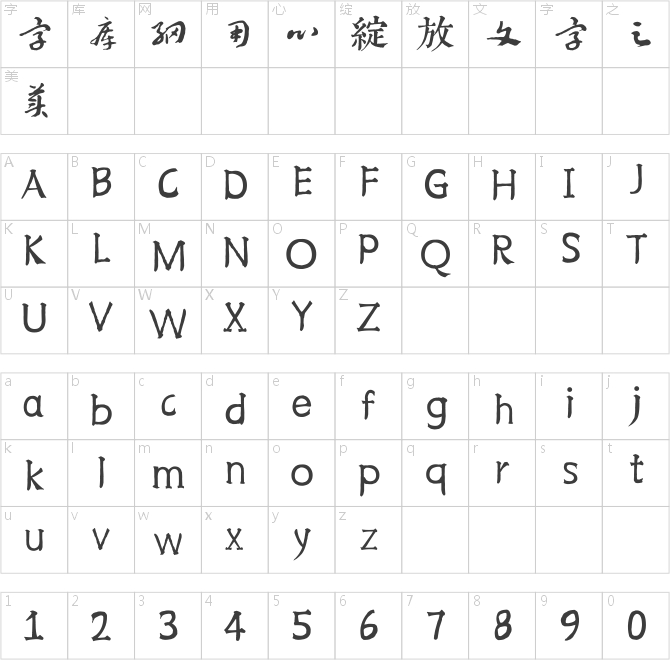
邯鄲
韓紹杰
注:本字庫為古籍千字文復刻書法小字庫,字符數(shù)量為1000余字,如有特殊需求,可以聯(lián)系邯鄲字庫韓紹杰為您訂制,也可以聯(lián)系本站客服為您轉(zhuǎn)答!王蘧常(1900年6月2日—1989年10月25日),字瑗仲,號明兩,別號滌如、甪里翁、玉樹堂主、欣欣老人,浙江嘉興人,中國哲學史家、歷史學家、著名書法家。其父王鈞畇為清光緒十五年舉人,工書法,博學。蘧常幼年受父影響,七歲時能作詩。早年曾從師沈曾植治學。1920年入無錫國學專修館。1927年去上海先后執(zhí)教于光華、大夏、復旦、交通等大學。 晚年致力于書法,精心研究漢簡,欲化漢簡、漢帛、漢陶于一冶,拓展了章草之領域。其書法作品在日本享譽極高,人稱“古有王羲之,今有王蘧常”。曾任上海交通大學、光華大學(今華東師范大學)、復旦大學教授,文史哲藝俱通,著作宏富。